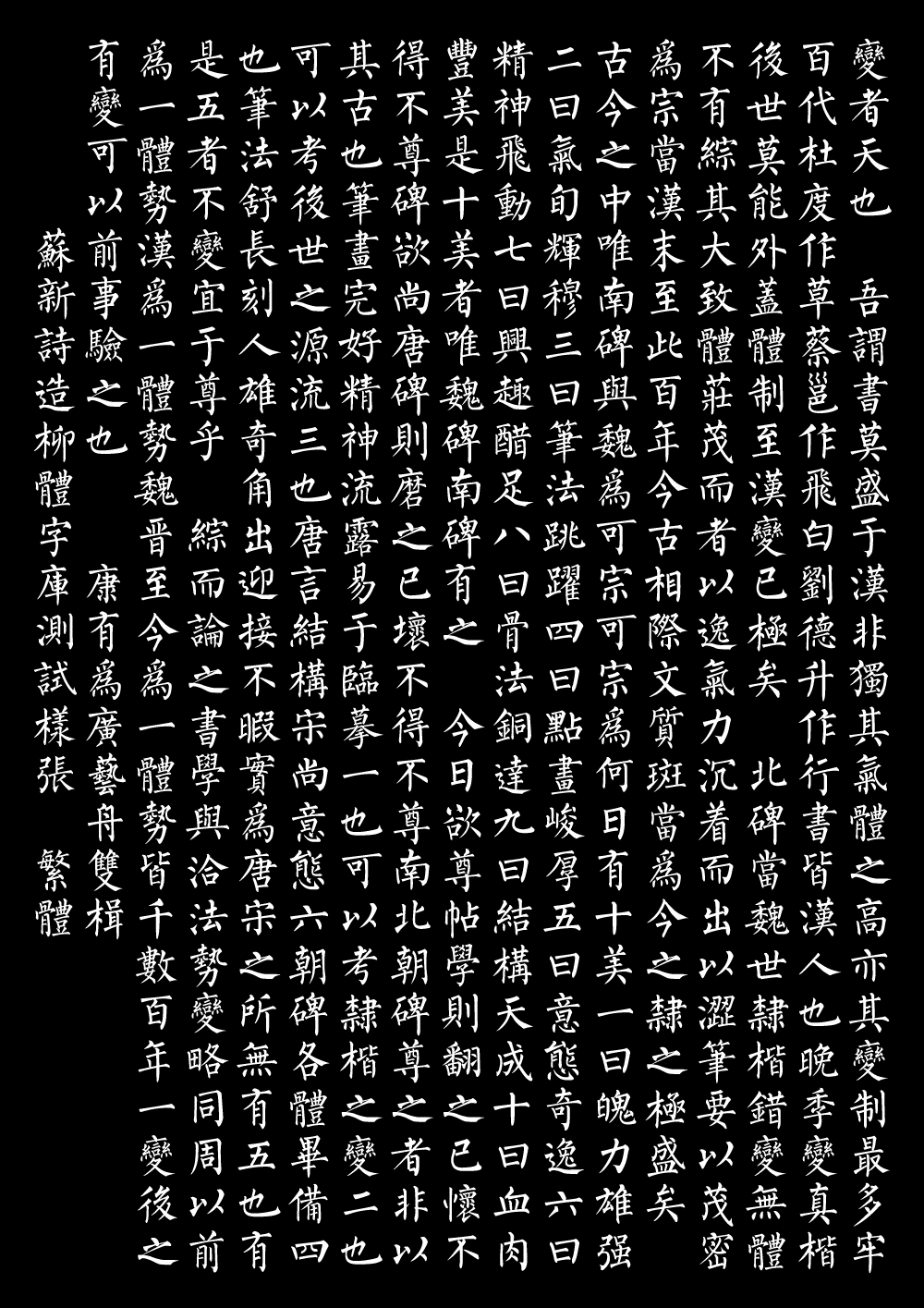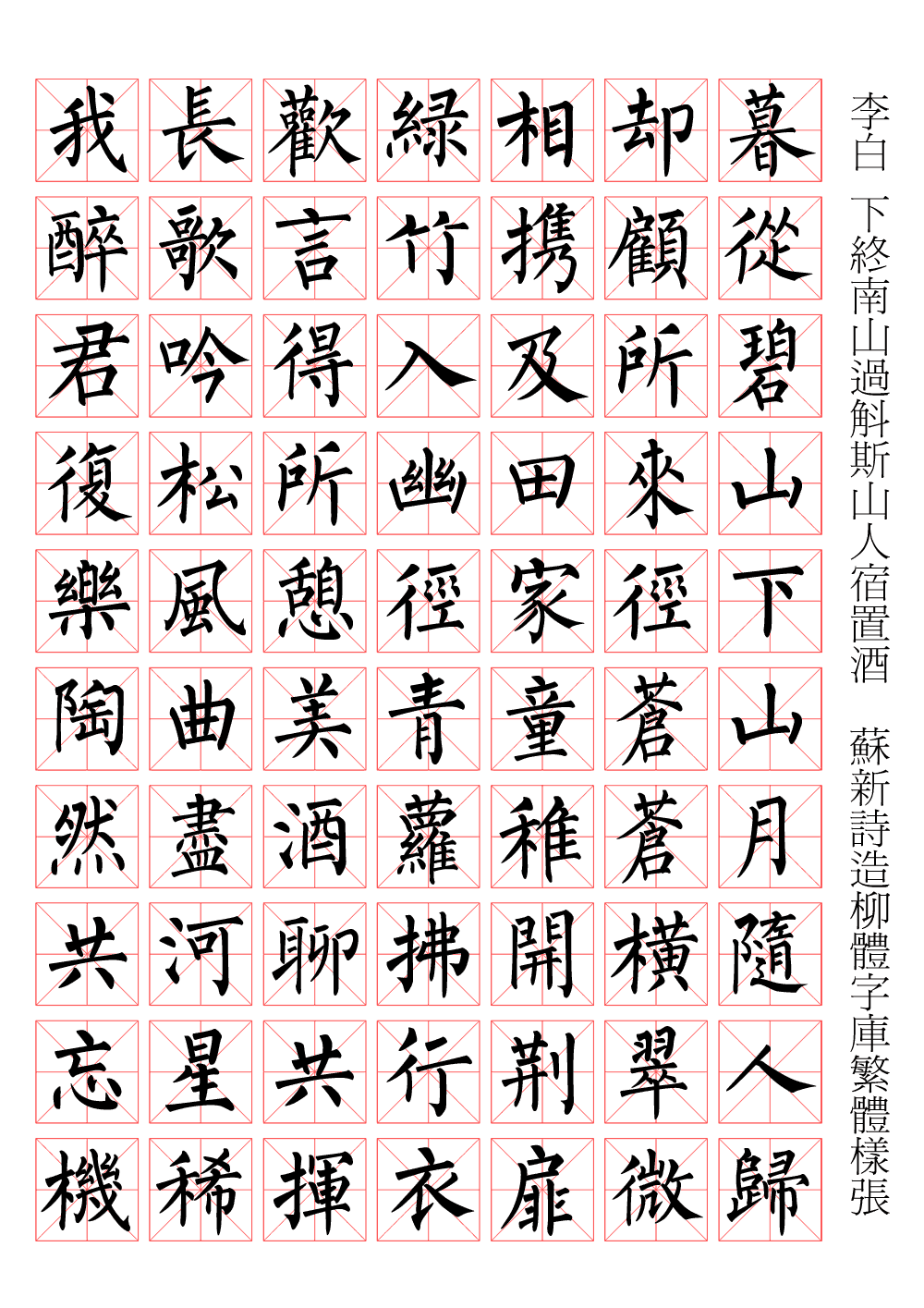
苏新诗:商丘小伙五年艰辛开发柳体字库
他让柳体字上了电脑字库,他被方正电脑公司称为中国首位独自开发整套中文字库第一人,他就是商丘市虞城县一名普普通通的青年苏新诗。
5月24日,苏新诗在虞城县他不足15平方米的“卧室工作间”,向记者讲述了5年来,他开发“新诗柳体字库”过程中的点点滴滴……
找不到柳体字库令他震惊
1964年,苏新诗出生于虞城县闻集乡一个教师家庭。受酷爱书法艺术的父亲熏陶,苏新诗从小就对书法产生了极大的兴趣,特别对笔画瘦硬、骨气凛然的柳体楷书更是情有独钟。
2000年,苏新诗突然想在电脑上用柳体字为朋友编排一个广告,却无论如何也找不到柳体字库。对此,苏新诗极为震惊。一位电脑方面的专家告诉他,造一个字库,首先得有熟悉柳体字的书法家把国家标准的1万多个字符(繁、简)一一写下来,接着还要扫描、数字化整合、修字、测试,是一项非常大的工程。尽管目前网上一个通用字库正常的价格是70万元。可现实情况却是:研究后,投入市场,别说70万元了,有可能5万元还没收回来就已经被盗版,所以,以营利为目的的公司都不愿做这种赔本的生意。
“难道柳体字永远无法‘走进’电脑世界吗?”苏新诗不甘心,决定自主开发“新诗柳体字库”。
5年艰辛完成柳体字库
打定主意后,苏新诗就批发来宣纸,买了扫描仪和电脑,开始了艰辛的“新诗柳体字库”开发之路。
“新诗柳楷简”、“新诗柳楷繁”两套字库,都要采用国标GB2312汉字编码制作,每套字库包含682个符号、6763个汉字,总字数1万多个。做字库时,这些字都要先用柳体逐个写一遍。5年来,苏新诗平均每天在电脑前工作10个小时,累计2万多个小时,因为白天上班,一般都在晚上做。“原来多明的眼睛,这会儿都快瞎了!”苏新诗的母亲说,“他房间的灯凌晨2点以前几乎就没关过,通宵也是常事。”
“我要求自己写出的每个字都是自己的最高水平,否则,我宁可写100遍。”苏新诗说。
字的问题解决了,接下来要面对的就是造字软件的问题。因为,把字用柳体写下来扫描到电脑上之后,还得用造字软件把它们“对号入座”,填充在相应的码位。
可是一般的造字软件,网上报价都在5万元以上,无奈,他只有在网上搜索免费的造字软件,并通过学习,对软件进行改装、组合、优化,慢慢地,一天也能编10来个字了。2005年年底,整套“新诗柳体字库”终于做完了。当看到自己开发的“新诗柳体字库”通过打印机从电脑中“爬”出来时,苏新诗哭了……
终于得到市场认可
字库造好后,苏新诗试着把自己用“新诗柳体字库”打印成的文件,制成图片传到了自己的博客上。没几天,他就收到了来自全国各地的广大网友的大量祝贺和赞扬,他们有一般的网友,也有书法爱好者,甚至还有书法界的名流。其中,中国著名书法家刘正成先生看到苏新诗做的字库后激动不已,专门给他发来了信件,表示感谢和敬意。
为了让自己的“新诗柳体字库”得到推广,苏新诗首先与方正电脑公司取得联系,希望通过他们得以在全国发行。方正电脑公司的工作人员感觉苏新诗是在开玩笑。他们非常清楚要开发一个字库需要几十名专职工作人员,耗费几年时间,花费几十万元资金才能完成。苏新诗说:“后来,他们要求我带着相关资料来到北京他们公司的造字部,看过我开发的字库后,他们公司造字部的一位负责人朱先生赞不绝口。”随后便与他签订了使用推广合同。
按照合同要求,苏新诗正对原来的“新诗柳体字库”的个别字在结构上进行了规范化修改,不用多久就可以最终完成。